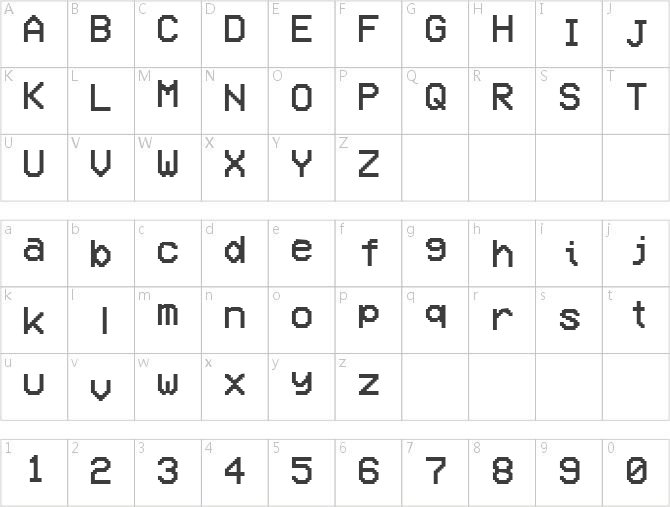
VCR_OSD_MONO_1.001 詳情頁
字體名稱: VCR_OSD
VCR_OSD_MONO_1.001
VCR_OSD_MONO_1.001介紹
VCR_OSD_MONO_1.001字體字庫是一款讓人賞心悅目、百看不厭的英文字體,適合各類廣告和產品包裝設計應用,字體大小0.07MB,格式為ttf字體,上傳用戶是FaYu,作者/版權方為未知